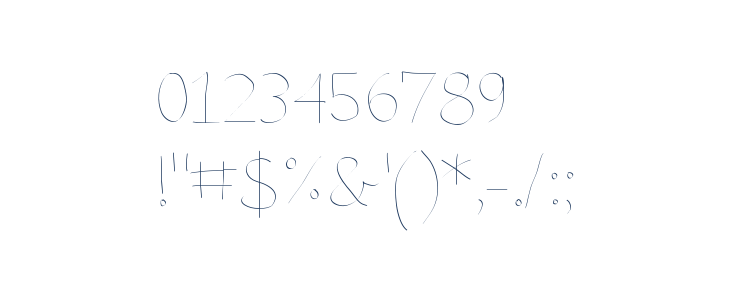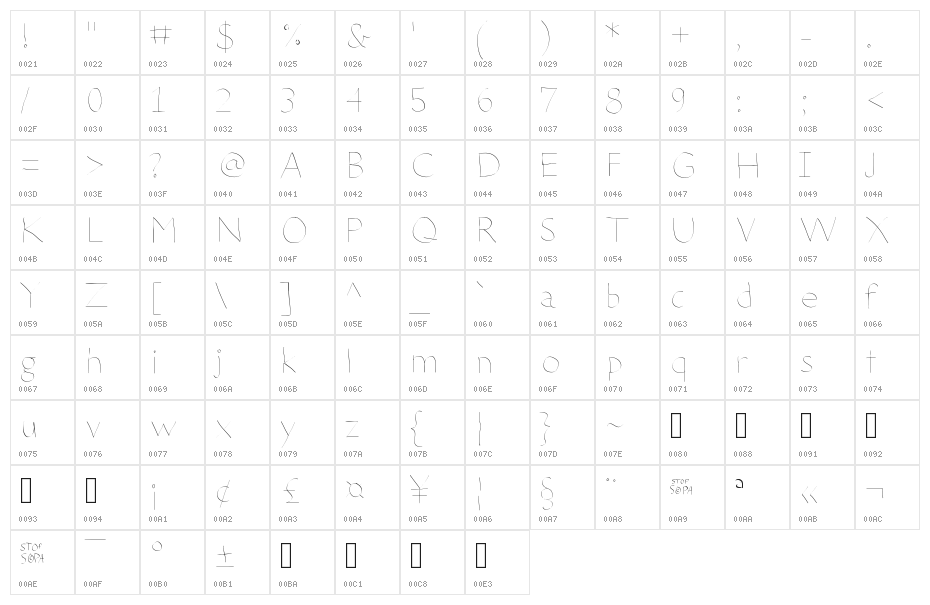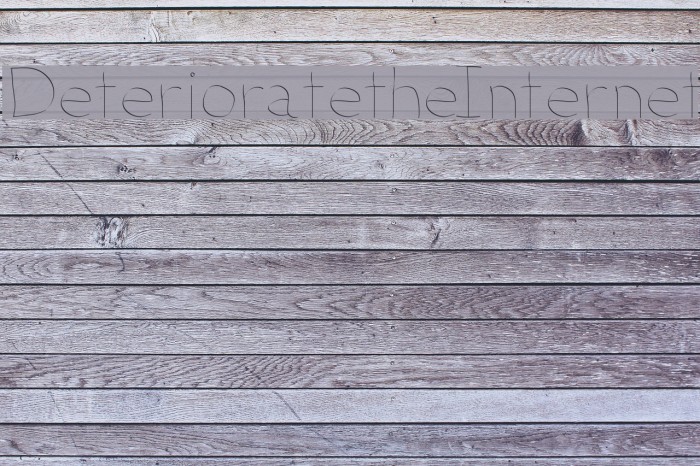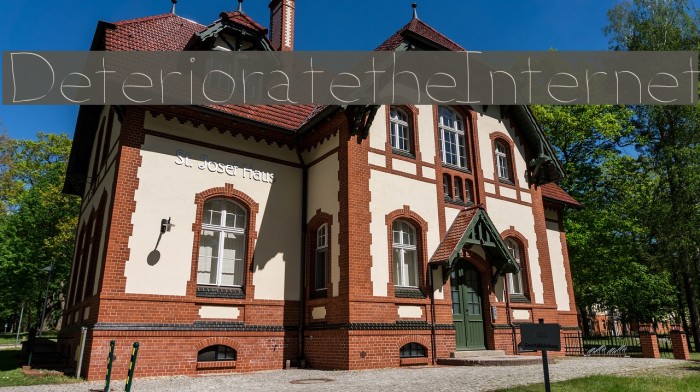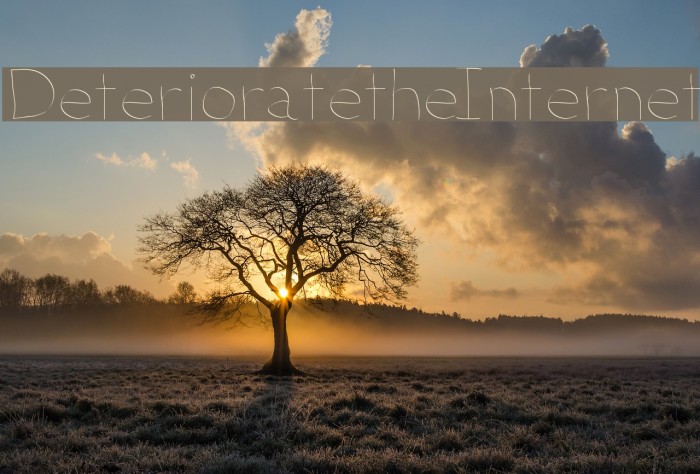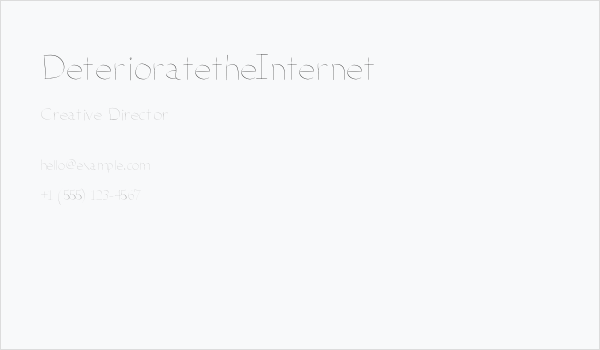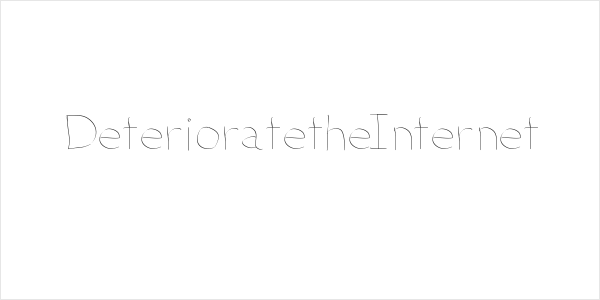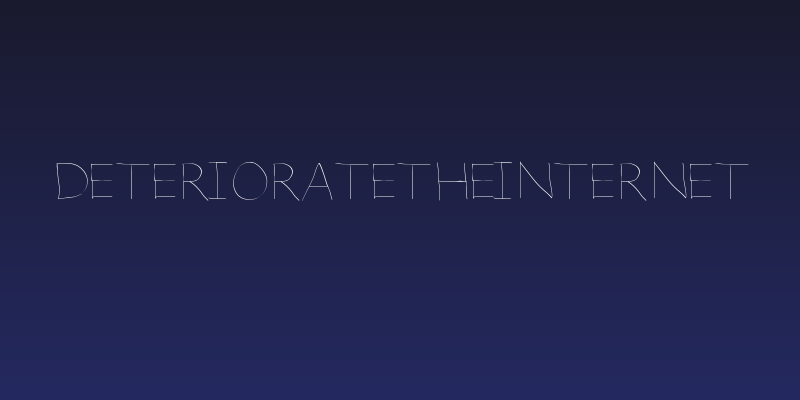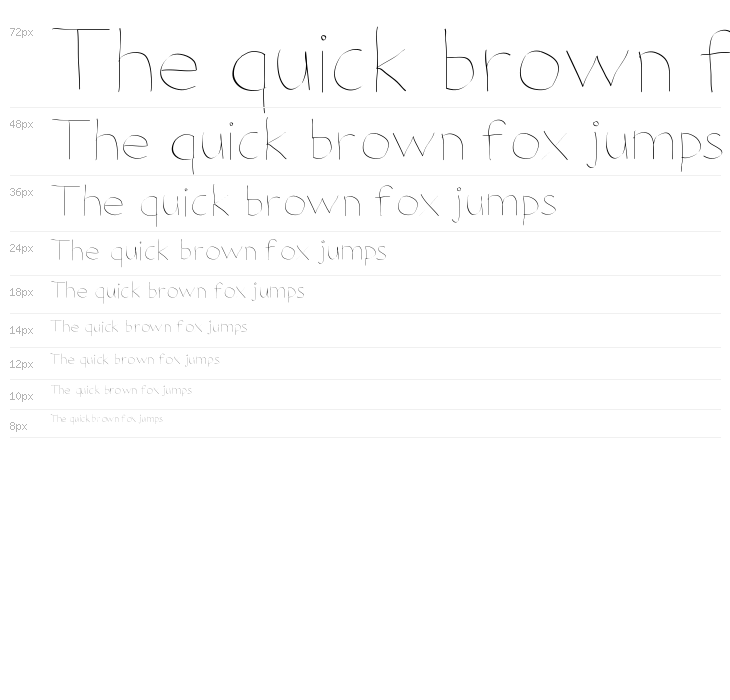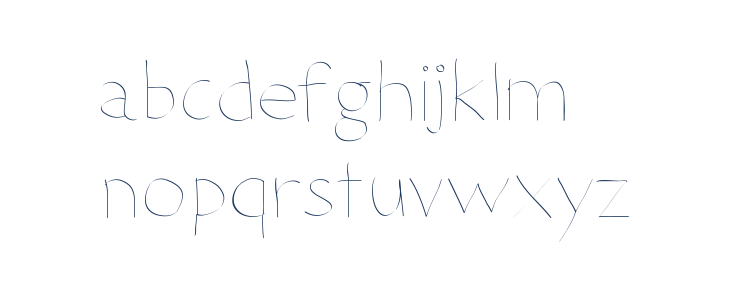
DeterioratetheInternet Font
| Stile generale | Elegant, Minimalist |
| Caso d'uso | Invitations, Branding, Logos |
| Progetti proposti | Ideal for wedding invitations, personal branding, elegant logos, and minimalist designs. |